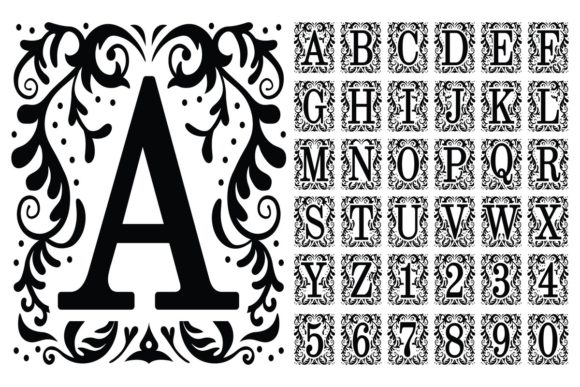
Vintage Monogram Letters
Jika anda sedang mencari aset berkualiti tinggi seperti Vintage Monogram Letters, pakej premium ini merupakan pilihan yang hebat untuk projek kreatif anda.
Sama ada anda mencipta produk POD (Print on Demand), jemputan perkahwinan atau grafik media sosial, Vintage Monogram Letters amat bersesuaian.